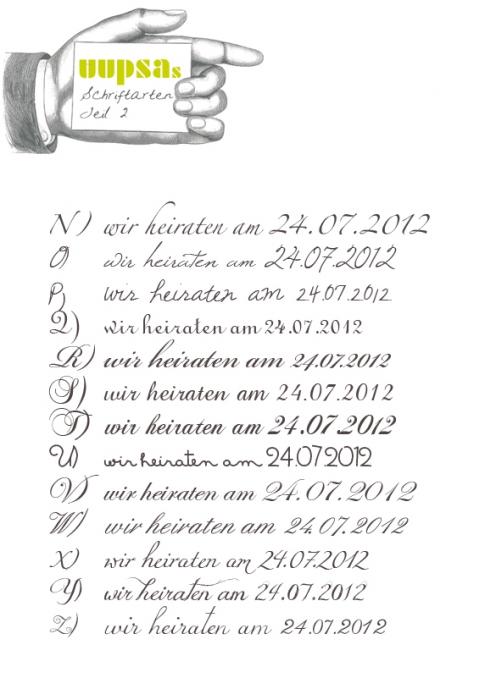
Suche Schreibschrift / Handschrift mit etwas schlechten Übergängen
ich suche für eine Freundin die Schrift P aus dem Anhang. Vielleicht habe ich ja Glück und jemand erkennt sie?
Hat jemand ev. auch einen Tip, für ein Schrifterkennungsprogramm oder ähnliches im Netz?
Die von Dir gesuchte Schrift kenne ich leider nicht. Aber unter diesem Link findest Du einen Artikel, der Dir sehr gut erklärt, wie Du Schriftarten herausfinden kannst, auch mit Hilfe von Schrifterkennungsprogrammen. Hilft Dir das weiter?
...ich weiß schon, die Schrift habe ich natürlich nicht vorgeschlagen.
Ich beobachte das mit den „Grusel-Schriften“ irgendwie überall, da ich ja nicht nur hier betrachte, was so an Schriften gesucht oder heruntergeladen werden. Da arbeitet man als Schrifdtgestalter seinen Font so sorgfältig, wie möglich aus, um einen sauberen Font zu bauen, und was laden sich die Leute herunter? Bei mir ist es unter anderem eine Schrift, für die ich mich fast schäme :nicken: , diese verbrochen zu haben - und dafür bekomme ich dann auch noch Dankesbriefe. :blabla: .